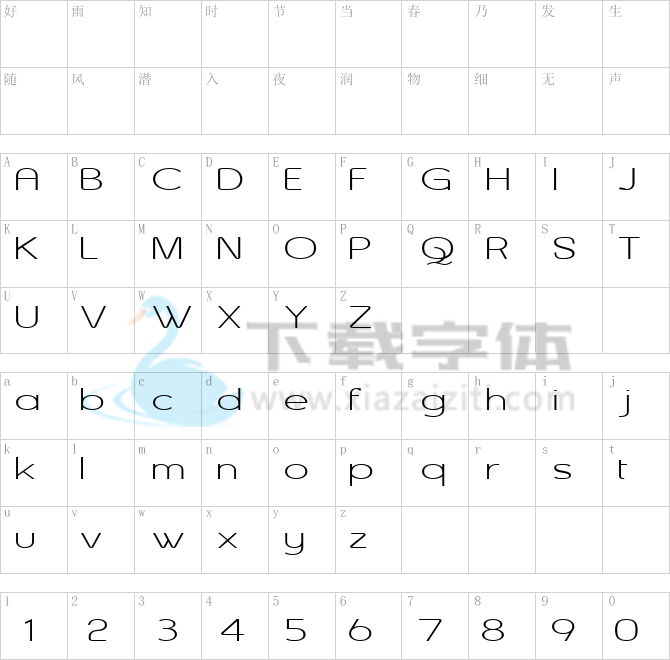
Asenine Wide.ttf字体下载,这款字体结构工整、笔画清晰,兼顾美观与易读性,适用于标题、正文、海报、包装、LOGO 等多种场景。字形优雅稳定,风格百搭耐看,适配日常排版与创意设计,让文字呈现更舒适、更具质感。Asenine Wide.ttf字体下载一笔一画,皆是细节,以均衡的比例、流畅的线条打造舒适视觉体验,字形端正大气,风格简约现代。无论是商业设计、品牌宣传还是日常排版,都能轻松驾驭,让文字更有格调与力量。Asenine Wide.ttf字体下载字体下载。
• 字体名称:Asenine Wide